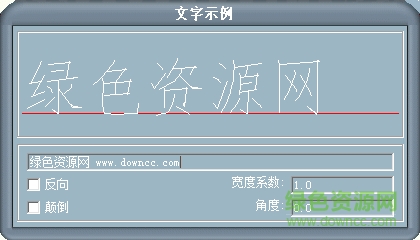
stjtbz是什么字體?stjtbz.shx字體是一款常見的交通標(biāo)志專用字體,該字體的長度和寬度都有一定標(biāo)準(zhǔn),可以用來制作交通標(biāo)志牌,有需要者快來綠色資源網(wǎng)下載吧!
該字體是交通部在2007年的高速公路交通標(biāo)志改造過程中的專用字體。是CAD專用,是.SHX格式,這種字體是以黑體為基礎(chǔ),正方形的黑體漢字;被仍然廣泛應(yīng)用于高速公路標(biāo)志標(biāo)牌的字體中。
筆劃寬度是字體高度的1/10;
數(shù)字的寬度是字體高度的6/10;
筆劃寬度是高度的1/6;
大小寫的拉丁字母不變。